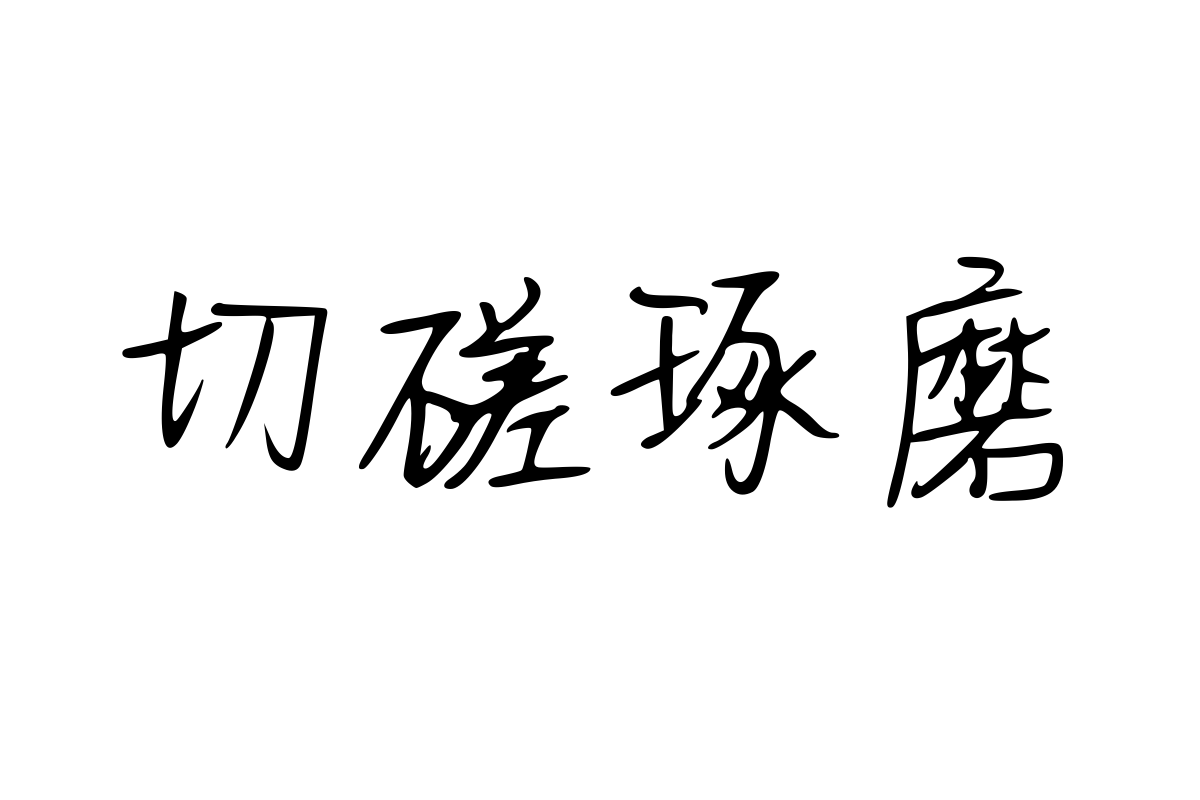
思雨字体-浮世苍凉体是一款具有独特风格和特色的中文字体。它采用了独特的字形设计,使得每个字都呈现出一种苍凉、忧郁的感觉。这种字体适合用于需要表达深沉、哀愁情感的场合,如诗歌、歌词、散文等。
思雨字体-浮世苍凉体的笔画粗细不一,既有粗犷豪放的线条,也有细腻柔和的笔触。这种对比使得字体更加生动有趣,也更易于阅读和理解。同时,它的字形结构紧凑,线条流畅,给人一种简洁明快的感觉。
此外,思雨字体-浮世苍凉体还具有一定的艺术性。它的字形设计独特,充满了创意和想象力。这使得它在视觉上更具吸引力,能够更好地表达作者的情感和思想。
总的来说,思雨字体-浮世苍凉体是一款具有独特风格和特色的中文字体。它适合用于需要表达深沉、哀愁情感的场合,同时也具有较高的艺术价值和观赏性。